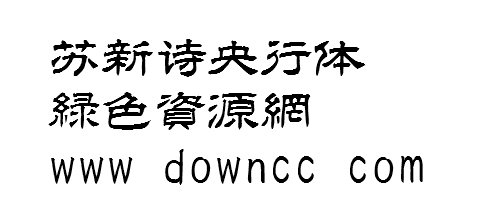
蘇新詩字體合集(10款)
蘇新詩字體打包收錄了蘇新詩現(xiàn)已推出的十款字體,有三款字體正在制作中,本系列字體大氣嚴謹,兼具藝術字體、手寫字體、行書字體等多種特色,為了方便用戶更好的體驗,綠色資源網(wǎng)帶來了最全的蘇新詩字體合體,免費下載體驗吧!
蘇新詩字體包括
蘇新詩柳楷
蘇新詩藝標簡
蘇新詩爨寶子碑簡
蘇新詩古印宋簡
蘇新詩毛糙體
蘇新詩雙勾體
蘇新詩卵石體
蘇新詩鼠標行書簡
蘇新詩央行體
蘇新詩指畫體
蘇新詩魏碑簡
蘇新詩大顏楷
蘇新詩仿魏繁
(后三款字體正在創(chuàng)作中)
蘇新詩介紹
蘇新詩河南商丘人,自幼受父親熏陶,酷愛書法美術,特別對筆畫瘦硬、骨氣凜然的柳體楷書更是情有獨鐘,多年筆耕不輟,臨習名家碑帖,真、草、隸篆諸體都有涉獵。
蘇新詩所研發(fā)的“蘇新詩柳楷體”已與方正公司合作,成為一款可以用于商業(yè)設計的書法字體,被稱為中國首位。